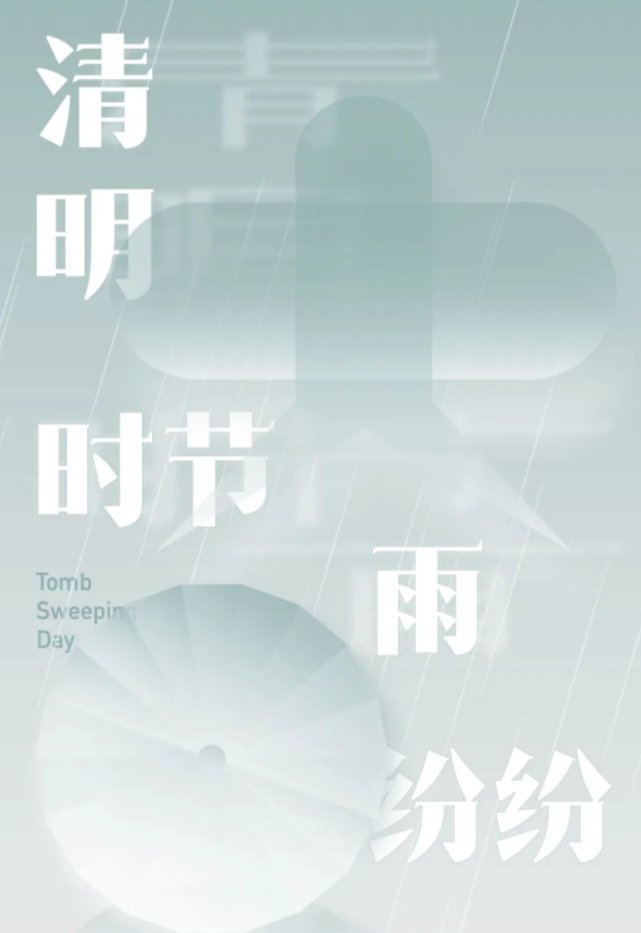
造字工房 咏宋体
造字工房咏宋体,字形稳重苍劲、笔势刚健,笔锋端正雄迈而又不失隽秀,横竖笔画对比强烈、刚柔相济,结构遒美健秀、规整端庄,收放自如。横画上的尖突处理与点画特点相呼应,具有极强的视觉张力。适用于广告大标题、宣传物料包装及个性品牌设计推广等环境。本字体为简体字库,采用OpenType/CID格式,Adobe-GB1-5编码。基于中华人民共和国GB2312-80字符集标准,另按需添加101个汉字。共收容字数6864CJK汉字,ASCII常用字符100个。